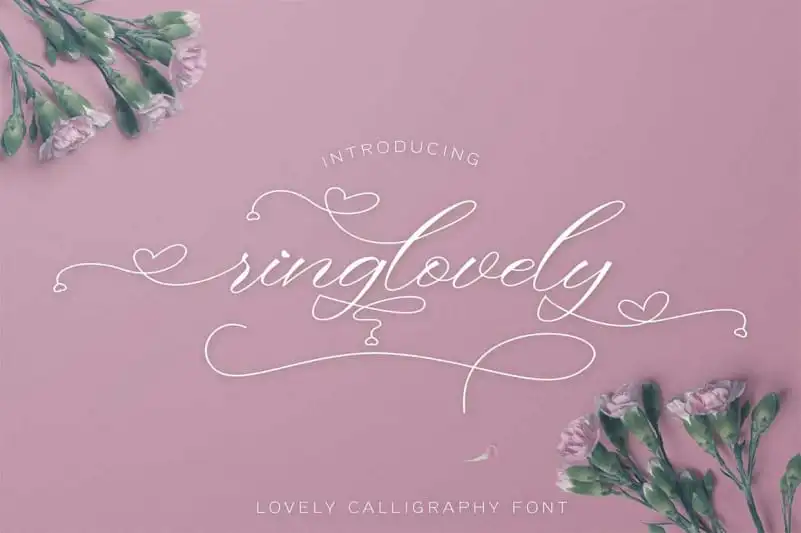
Ringlovely Calligraphy Font – Download Grátis
Ringlovely Calligraphy Font é uma elegante fonte script que oferece uma gama completa de caracteres para projetos visuais diversos. Perfeita tanto para ilustrações quanto para logomarcas, cartões de casamento, capas de livros, e até mesmo desenhos fashion, essa fonte permite que você combine seu estilo personalizado com outros tipos para criar trabalhos realmente memoráveis. Adicionalmente, a característica PUA (Propriedade Universal de Ascender) torna esta fonte ainda mais versátil. Com ela, é simples acessar todos os caracteres e swashes facilmente. O design inclui linhas suaves, oito níveis variáveis de linha-base para garantir um layout harmonioso e atraente, além de belas formas góticas e alternativas impressionantes. Ringlovely Calligraphy Font mantém sua influência clássica da calligrafia ao mesmo tempo que se destaca por sua modernidade. Se apaixonar pela fonte é como adicionar um toque final único a seu projeto, tornando-o mais memorável e profissional. Para qualquer tipo de projeto em que você esteja buscando uma paleta única de estilos, Ringlovely Calligraphy Font é a escolha ideal.